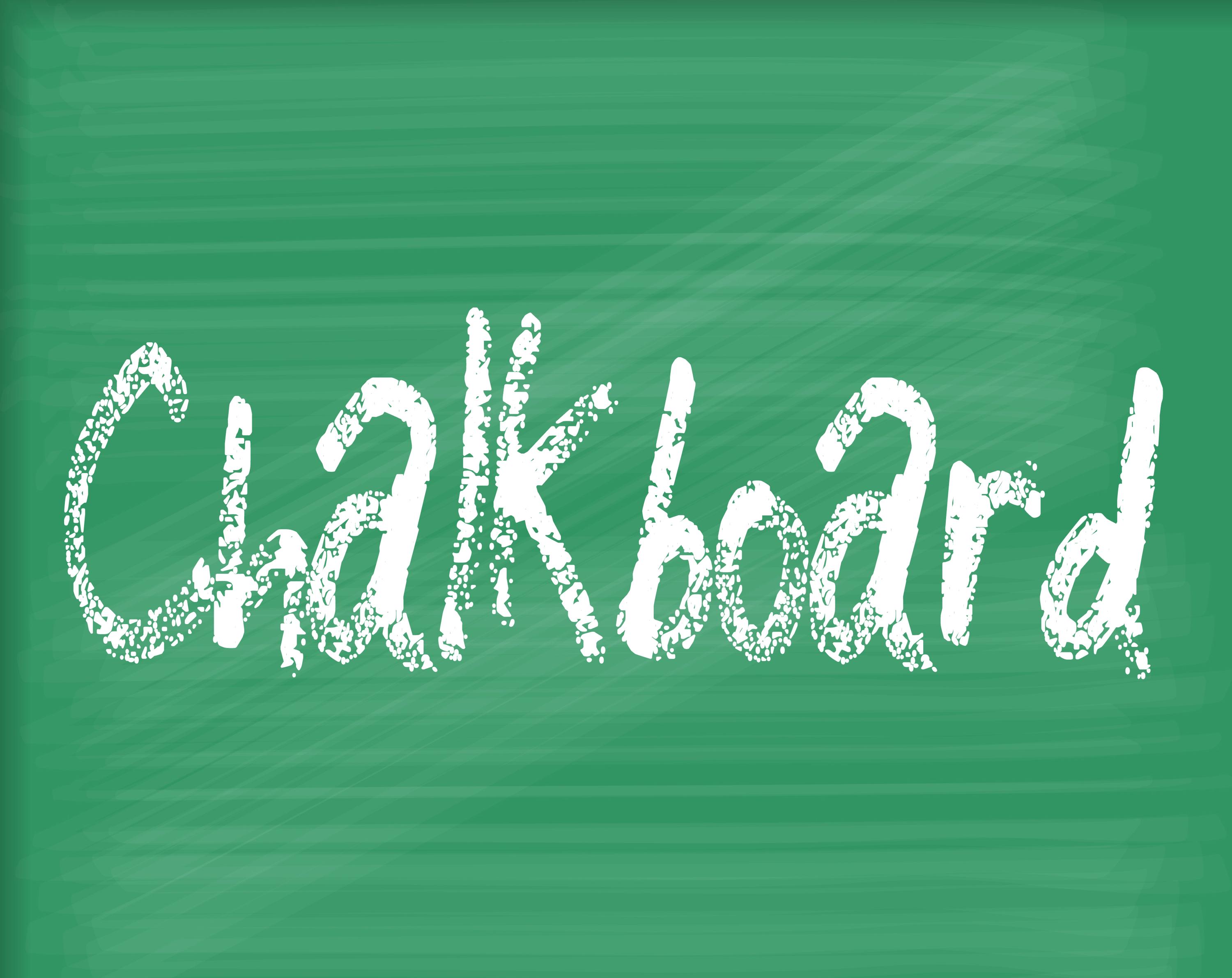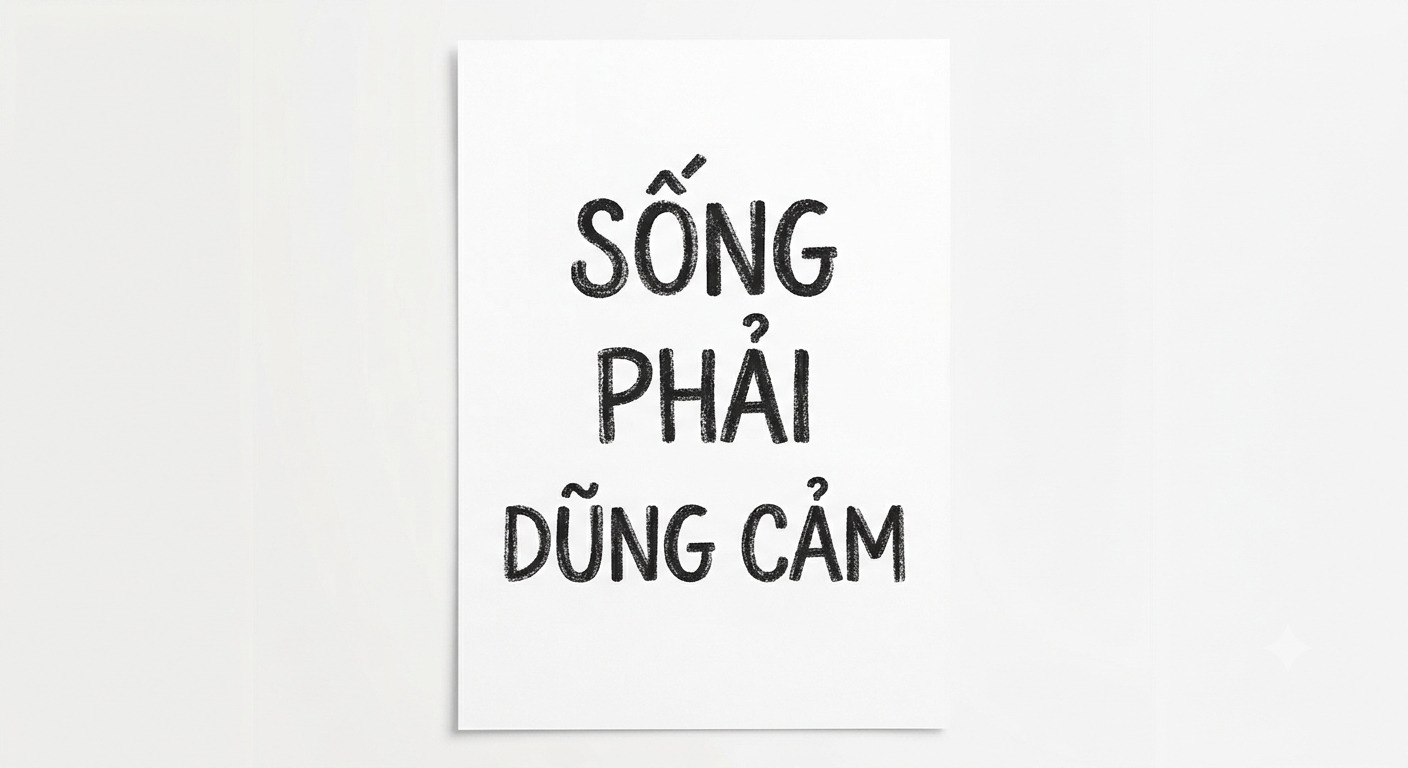
Nhiều nhà thiết kế khi sử dụng Chalkboard Font thường gặp lỗi thiếu dấu tiếng Việt, ký tự hiển thị không đồng đều hoặc nét chữ bị nhòe khi in trên menu, bảng hiệu và hộp quà tặng. Những lỗi này làm mất đi vẻ tự nhiên, thủ công đặc trưng của kiểu chữ viết bảng, khiến ấn phẩm thương hiệu thiếu sự chỉn chu trong quá trình sản xuất.
Chalkboard font là gì?
Chalkboard font là một gia đình phông chữ thuộc dòng Handwritten (viết tay), được tạo ra nhằm mô phỏng lại nét chữ viết bằng phấn trên bảng đen một cách tự nhiên và sinh động. Đây là bộ phông được đánh giá cao về khả năng hiển thị rõ ràng, giữ được sự vui tươi, gần gũi nhưng vẫn đảm bảo sự chỉn chu hơn so với nhiều phông viết tay khác. Chalkboard SE thường xuất hiện trong các dự án thiết kế cho giáo dục, thực đơn nhà hàng, bao bì sản phẩm thủ công hoặc các ấn phẩm truyền thông dành cho thiếu nhi.
Bộ phông này bao gồm nhiều biến thể khác nhau để phục vụ đa dạng nhu cầu trình bày. Trong đó, Font Chalkboard SE Light mang đến nét chữ thanh mảnh, nhẹ nhàng, phù hợp cho các đoạn văn bản hướng dẫn hoặc thông tin chi tiết. Ngược lại, Chalkboard SE Bold Font với nét chữ dày dặn, vững chãi lại là lựa chọn lý tưởng cho các tiêu đề chính, slogan hoặc logo để tạo điểm nhấn thị giác mạnh mẽ. Bản việt hóa được cung cấp đã xử lý kỹ thuật Kerning, giúp các ký tự tiếng Việt có dấu hiển thị ổn định và hài hòa trên nhiều bề mặt vật liệu in ấn.
6 ứng dụng font Chalkboard Việt hóa trong thiết kế và in ấn
Với phong cách chữ viết tay mô phỏng nét phấn bảng, font Chalkboard Việt hóa mang lại cảm giác gần gũi, sáng tạo và phù hợp với nhiều thiết kế bao bì, quà tặng doanh nghiệp:
- Thiết kế menu và bảng hiệu nhà hàng: Font Chalkboard phù hợp với các quán cafe, tiệm bánh, nhà hàng phong cách vintage hoặc thủ công. Kiểu chữ mô phỏng nét phấn giúp không gian thương hiệu trở nên thân thiện hơn.
- Sản xuất quà tặng giáo dục và học đường: Chalkboard có thể ứng dụng trên sổ tay, bình giữ nhiệt, túi vải canvas hoặc vật phẩm tặng học sinh, sinh viên trong các chương trình trường học.
- Thiết kế bao bì thực phẩm Handmade: Font chữ này phù hợp để in nhãn trà, mật ong, mứt, bánh thủ công hoặc sản phẩm Organic, giúp bao bì thể hiện phong cách tự nhiên và gần gũi.
- Trang trí backdrop và POSM sự kiện: Các tiêu đề dùng Chalkboard trên bảng thông tin, khu vực check-in hoặc ấn phẩm sự kiện giúp tạo điểm nhấn sáng tạo, phù hợp với các chương trình cộng đồng.
- In thiệp mời và thiệp cảm ơn: Những câu chúc ngắn bằng Chalkboard giúp thiệp tri ân, thiệp sự kiện hoặc voucher mang phong cách cá nhân hóa hơn.
- Khắc laser quà tặng gỗ: Logo hoặc tên người nhận sử dụng font Chalkboard khi khắc trên gỗ tre, gỗ tự nhiên giúp sản phẩm có nét thủ công và độc đáo.
5 lưu ý khi sử dụng font Chalkboard Việt hóa
Để font Chalkboard Việt hóa giữ được nét tự nhiên khi ứng dụng vào sản xuất thực tế, designer cần chú ý:
- Kiểm soát độ tương phản màu sắc: Chalkboard thường phù hợp với nền tối như đen, xanh rêu hoặc nâu gỗ. Khi sử dụng trên nền sáng, nên chọn màu chữ đậm để tăng khả năng nhận diện.
- Tối ưu đường Path khi gia công bế nổi: Chuyển đổi font Chalkboard sang dạng vector giúp xử lý các chi tiết nét phấn chính xác hơn, hỗ trợ quá trình dập nổi logo hoặc slogan trên hộp giấy.
- Điều chỉnh độ dày nét khi in: Một số chi tiết mô phỏng nét phấn có thể khá mảnh. Khi in trên giấy Kraft, vải canvas hoặc bề mặt nhám, cần cân chỉnh Stroke phù hợp để hạn chế mất nét.
- Kiểm tra dấu tiếng Việt: Các ký tự có dấu cần được rà soát để dấu thanh không bị chạm vào đường nét trang trí, giúp bố cục chữ cân đối hơn.
- Sử dụng cho nội dung ngắn: Chalkboard phù hợp với logo, tiêu đề hoặc câu chúc ngắn từ 2-5 từ. Với đoạn văn bản dài, nên kết hợp cùng font chữ đơn giản hơn để tăng khả năng đọc.